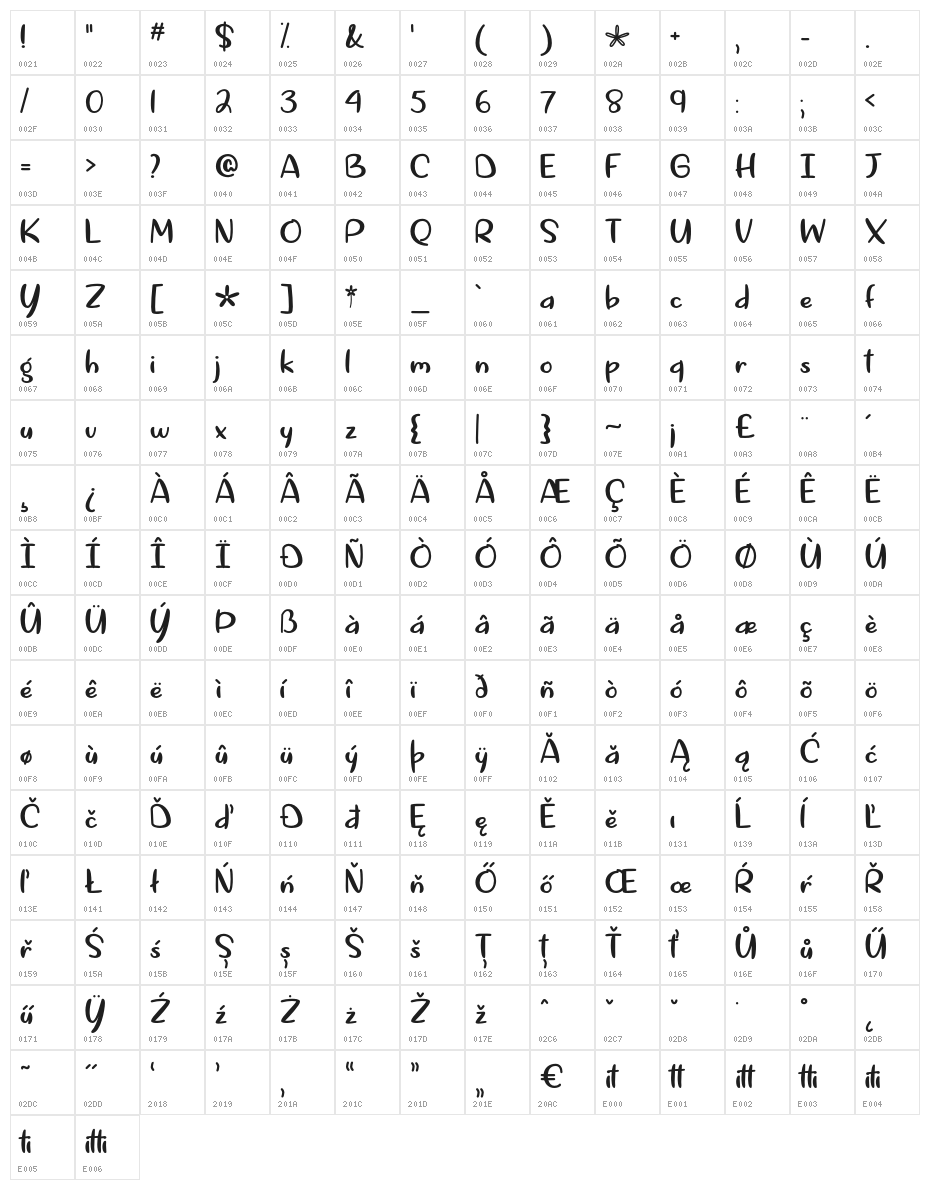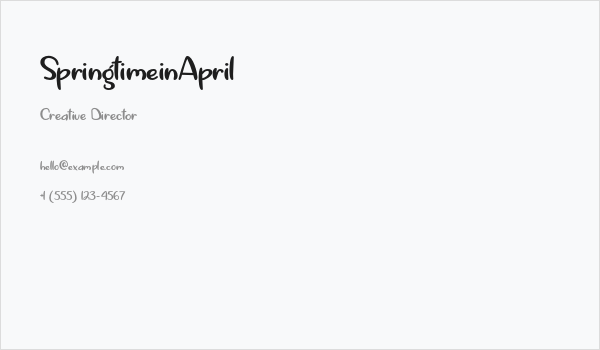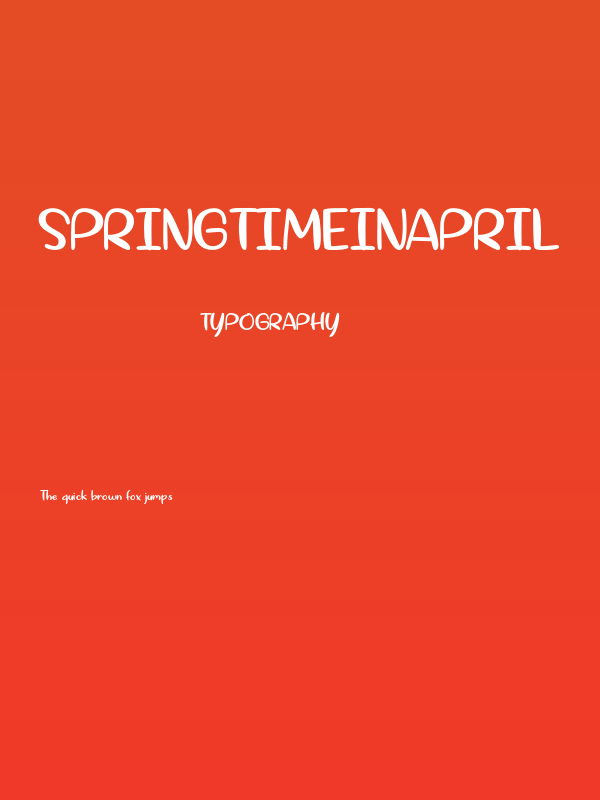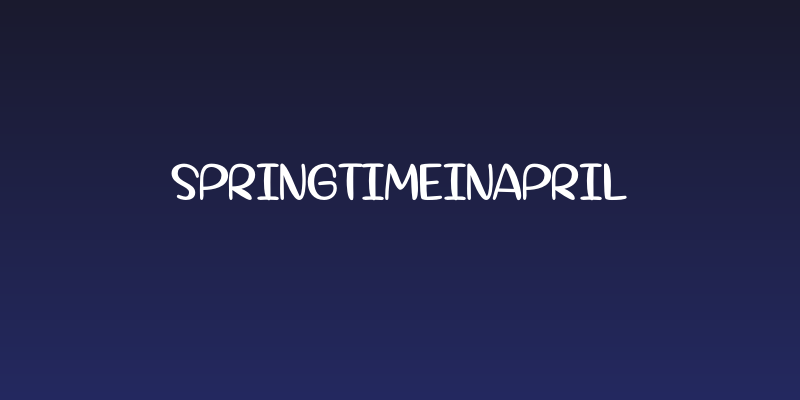
SpringtimeinApril Font
| Gesamtstil | Casual, Playful |
| Anwendungsfall | Headlines, Informal text, Creative projects |
| Vorgeschlagene Projekte | Ideal for greeting cards, children's books, playful branding, and social media graphics. |